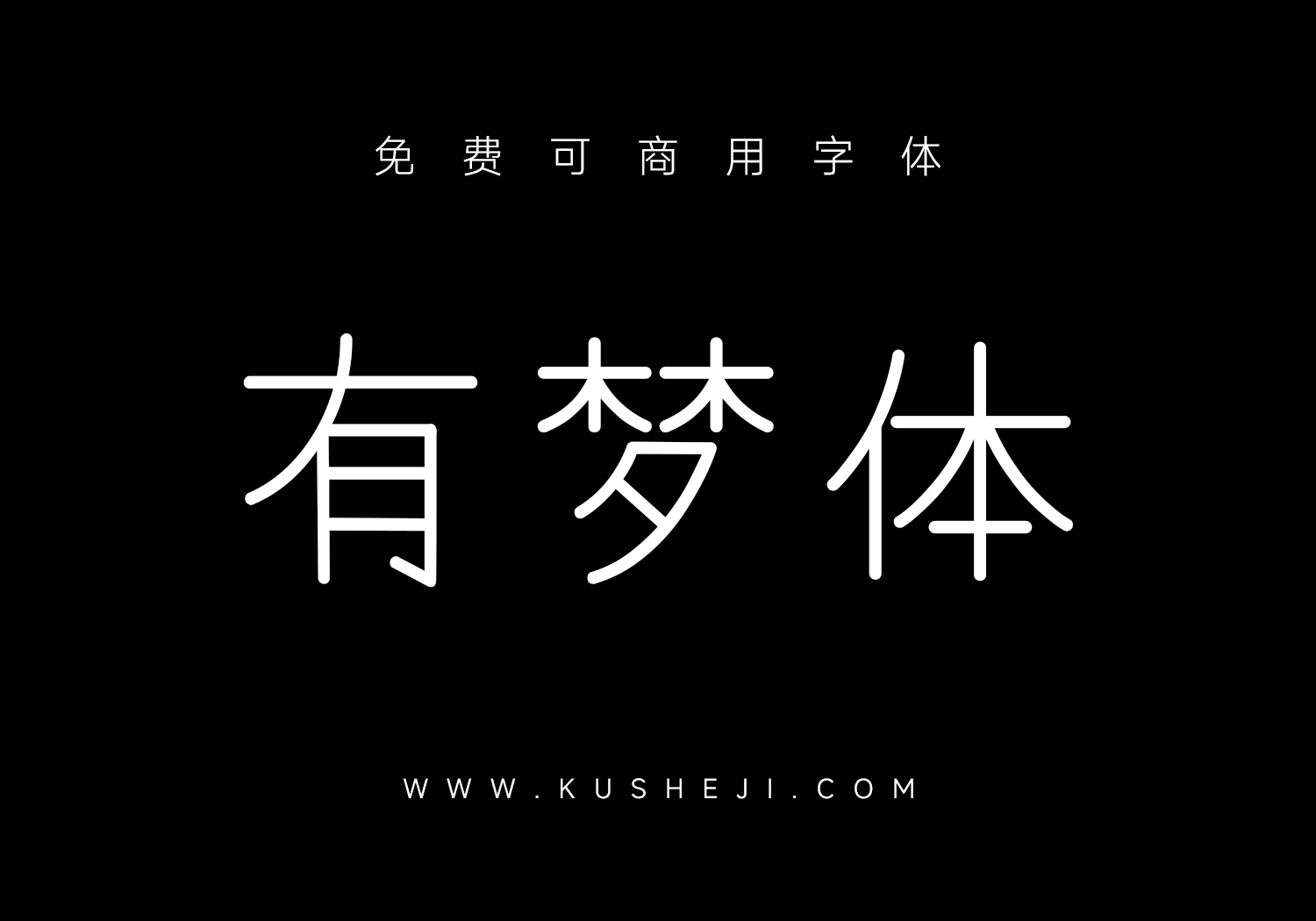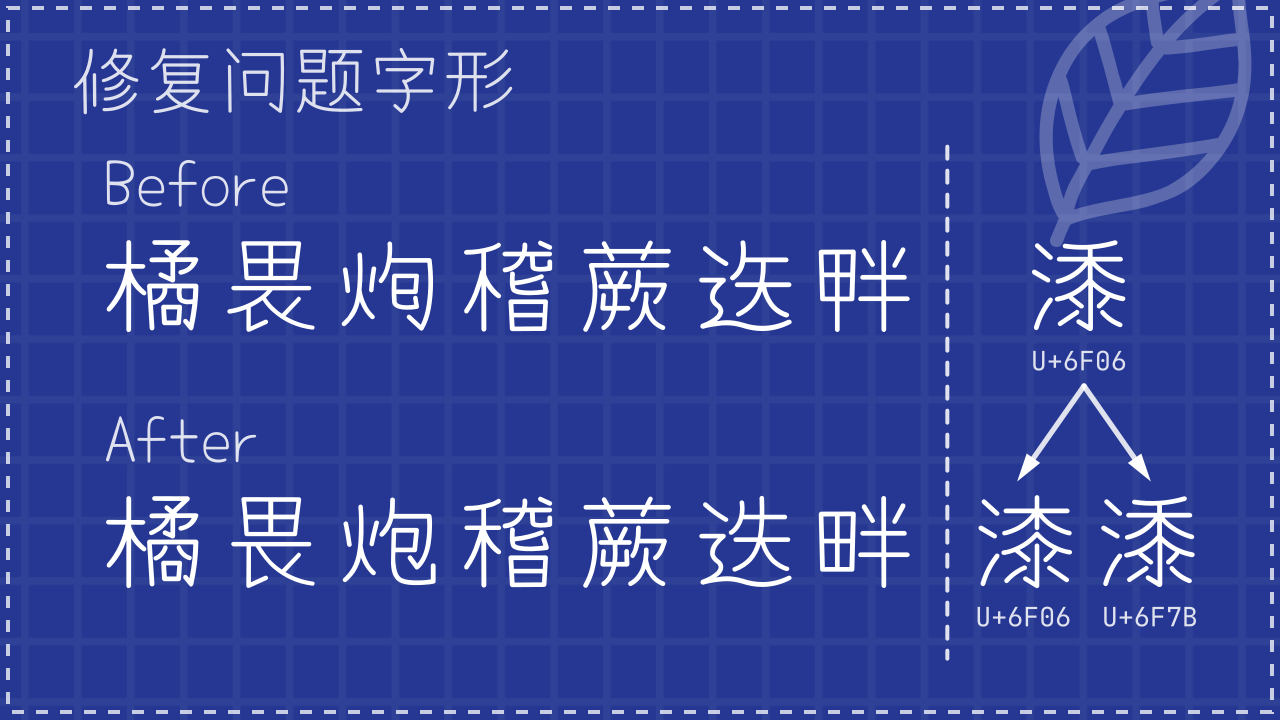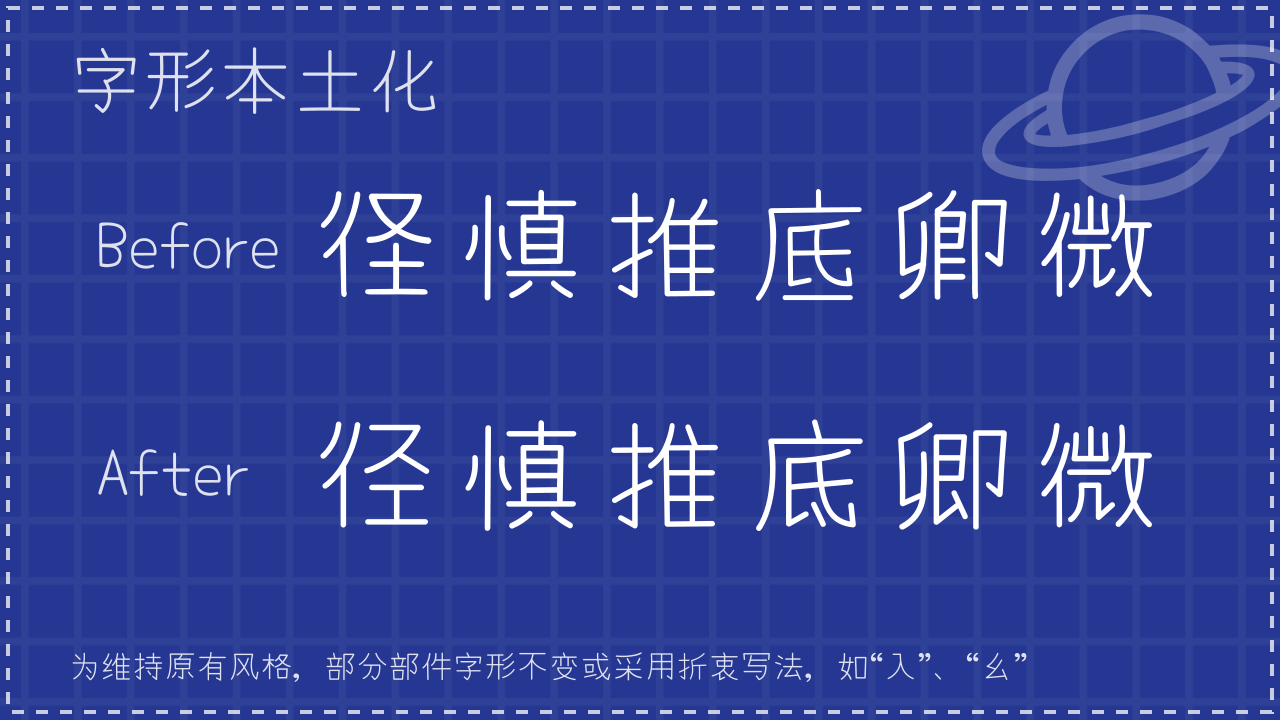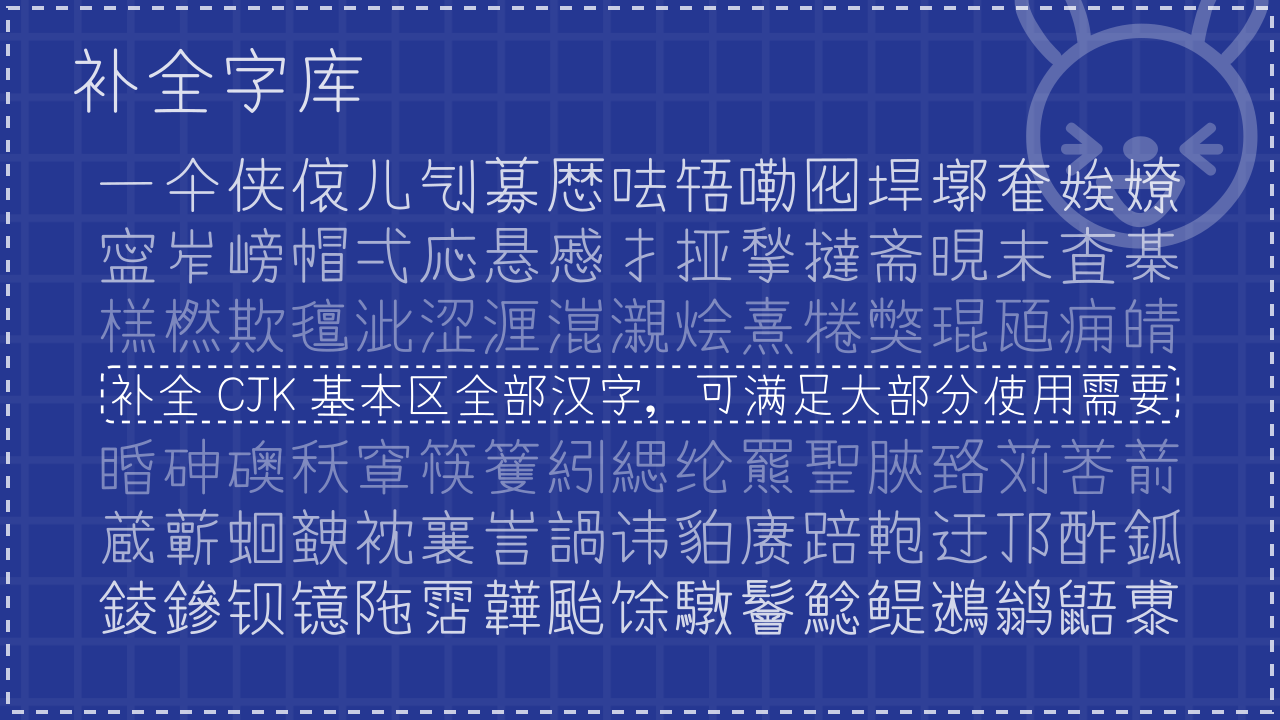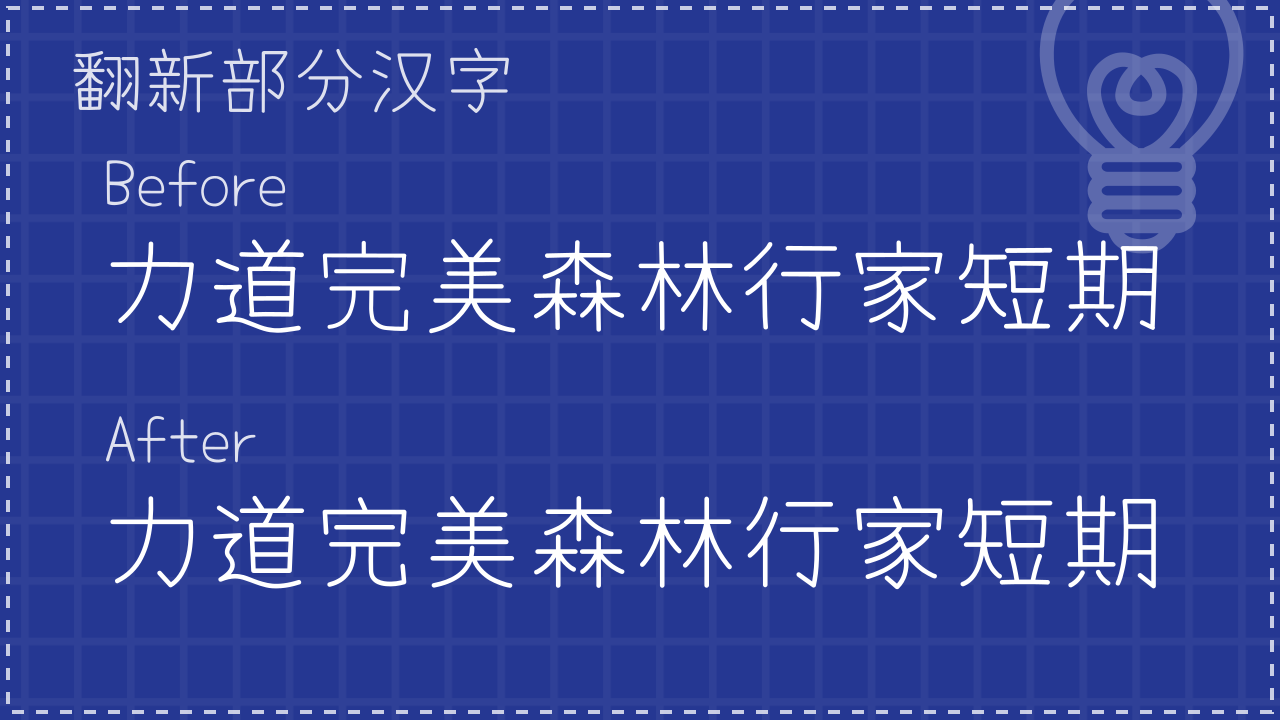
有梦体由 Yomogi 字体二次开发而成,是一款极具文艺气息的字体。
1. 补全字库
补全 CJK 基本区内全部汉字,可满足大部分使用需要。
2. 字形本土化
将大部分汉字调整为更符合陆标的字形,少部分汉字或部件为维持原有风格,保留原有字形或采用折衷写法。
3. 翻新部分汉字
翻新原字体当中部分风格差异较大的汉字,加强风格一致性。
4. 修复问题字形
修复原字体中一些笔画或码位存在问题的汉字。